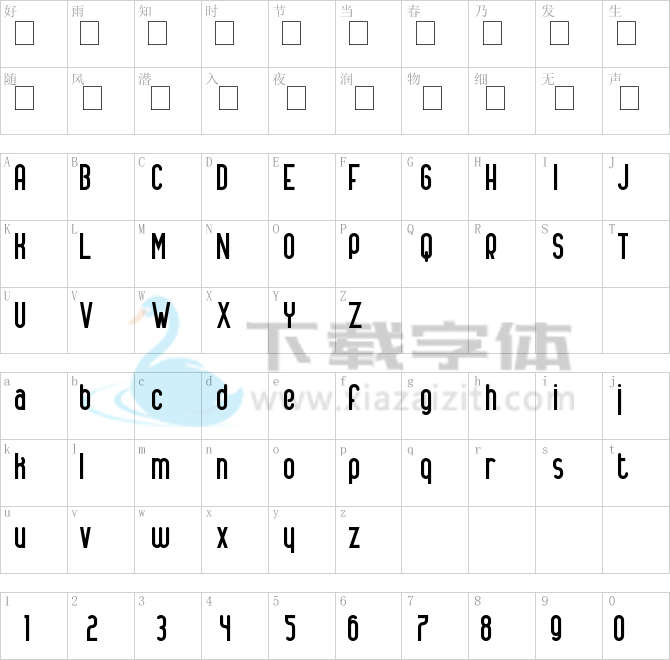
Alanus.ttf字体下载,这款字体结构工整、笔画清晰,兼顾美观与易读性,适用于标题、正文、海报、包装、LOGO 等多种场景。字形优雅稳定,风格百搭耐看,适配日常排版与创意设计,让文字呈现更舒适、更具质感。Alanus.ttf字体下载一笔一画,皆是细节,以均衡的比例、流畅的线条打造舒适视觉体验,字形端正大气,风格简约现代。无论是商业设计、品牌宣传还是日常排版,都能轻松驾驭,让文字更有格调与力量。Alanus.ttf字体下载字体下载。
• 字体名称:Alanus